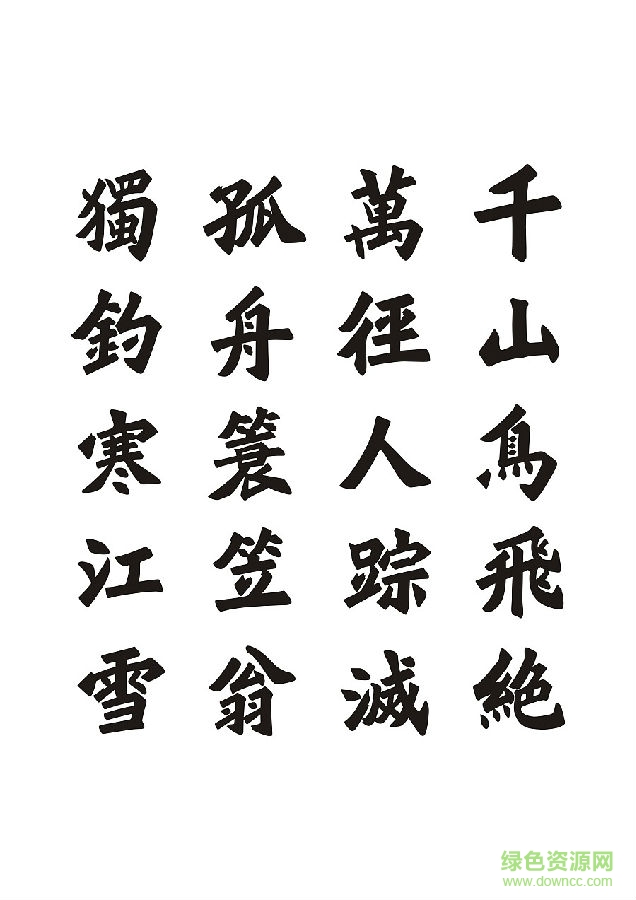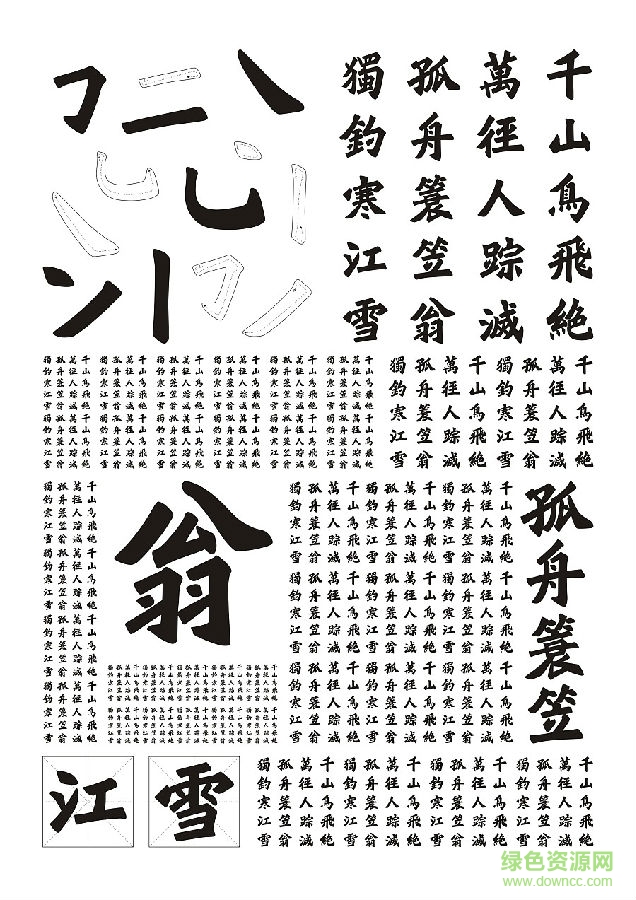
彥辰魏楷字體是彥辰字體中的其中一款,這款字體非常的氣派,每一筆都蒼勁有力,每一個(gè)字型都像一幅畫一樣,有需要的就來(lái)綠色資源網(wǎng)下載吧!
作品融合了張猛龍及趙之謙的書風(fēng),以碑+帖結(jié)合的方式來(lái)展開字形創(chuàng)作,力求呈現(xiàn)左緊右松、上緊下松、左收右放、上收下放的字形張力,傳達(dá)作者對(duì)書法字形和平面構(gòu)成的思考與探索。